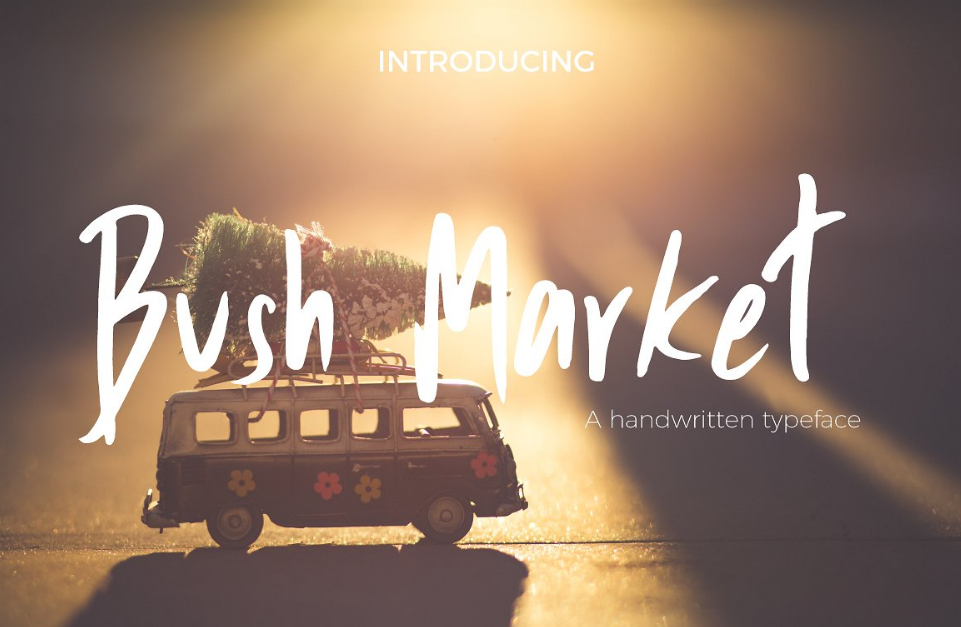
Introduzimos Bush Market Script Font! Esta elegante e versátil fonte foi criada pelo designer PARAMAJAN e é uma opção premium disponível para quem busca personalidade nos seus projetos digitais. Lançada originalmente no CreativeMarket, agora você pode adquiri-la gratuitamente hoje em seu download. Bush Market oferece um toque de autenticidade ao incorporar elementos da escrita a mão, criando um tipo script que transmite uma vibe acelerada e vibrante. Composta para quem busca personalização e expressão no design do texto, esta font é ideal para gráficos interativos, logotipos agressivos ou qualquer outro projeto em que você deseje transmitir um tom alegre e energético. Seja você designer de gráficos ou criador de conteúdo digital, Bush Market Script Font é uma excelente escolha para enriquecer sua paleta de ferramentas. Lembre-se, esta fonte permite que o seu trabalho seja não apenas visualmente impactante, mas também transmita um sentido vibrante e atemporal através do poder da escrita.